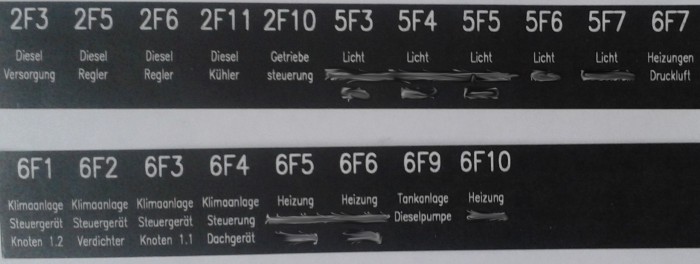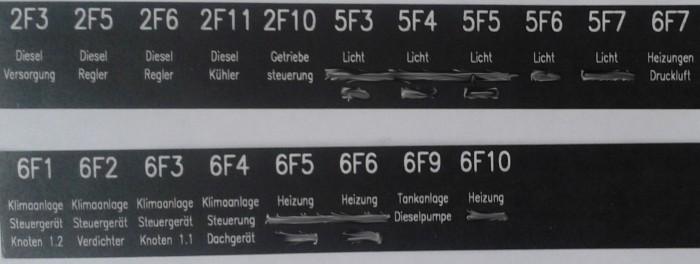
Suche Schrift, ursprünglich verwendet von ELIN
ich suche eine Schriftart die ich auf der Beschriftung einer Sicherungstafel (siehe unten) gefunden habe. Diese Tafel wurde von (VA TECH) ELIN EBG erstellt und beschriftet. Es handelt sich um eine schmale, serifenlose Schrift. Besonderes Merkmal ist die 3.
Ich habe bereits auf verschiedenen Wegen versucht die Schrift online erkennen zu lassen, leider ohne Erfolg. Auch hier in der Schriftenbibliothek bin ich nicht fündig geworden. Vielleicht kann mir von Euch jemand helfen, würde mich sehr freuen! :bow:
DIN Engschrift vermute ich. Zu kaufen gibt es sie zum Beispiel hier.
So weit ich weiß, gibt es die Schrift in verschiedenen Digitalisierungen. In der Wikipedia gibt es ein Bild von einem Stempel zu sehen, der die gewünschte Form der 3 verwendet.
... nicht ganz. Es wird eine Hausschrift eines Graviermaschinen-Herstellers sein.
sind ähnlich, welche genau davon es ist, hab ich jetzt nicht geschaut.
Als digitalisierte Computerfonts wird es die wohl kaum geben.
Was Du meinst vmtl. ist die DIN-Neuzeit-Grotesk nach ... *krustchel* DIN 30.640. Das ist aber keine DIN1451 sondern eine ge-DIN-te Neuzeit Grotesk. Und diese hat ein doppelstöckiges kleines a.
Diese Schrift habe ich sehr oft auf Typenschildern (Großküchen, Blitzschutz) und auf kleinen Warnschildern der E-Werken in den Haushalten gesehen. Subjektive Zuordnung: (Fast?) Alles mit Elektrizität von deutschen Herstellern und bis in die 1970er.
Eher umgekehrt. Solche Schilder wurden (und werden) standardmäßig in mehrschichtige Kunststoffplatten wie diese graviert:
und hierbei wear das sehr wahrscheinlich die Standardschift, die, weil sie der DIN-Schrift am ähnlichsten war, i.d.R auch verwendet wurde. Daher begegnet einen diese Schrift mit der von der DIN-Schrift abweichenden 3 nahezu überalkl, wo wetterfeste Schildere benötigt werden. und das eben schon nlange vor der Zeit, in der man überhaupt außerhalb des Druckgewerbes Satzschriften verwenden konnte
Demzufolge wird wohl kaum eine aktuelle Computerschrift als Basis geDINt haben.
Die von mir genannten Schriften sind keine Computerschriften, denn dazu sind diese zu alt. Mit Deinem Argument müsste man auch die Schriften nach DIN 1451 und anderen Normen ausschließen.
Gut, schließe ich auch die DIN 1451 und DIN16/DIN17 aus, und behaupte einmal, dass hier die Schriften beim Hersteller der Messing-Schablonen (was durchaus auch eines der großen Schriftgießereien gewesen sein kann) speziell hierfür entworfen worden sind. Dabei natürlich die Normschriften im Hinterkopf, jedoch das Normblatt auf dem Zeichentisch liegen zu haben.
Ihr werdet lachen, aber diese Beschriftung ist garnicht geprägt sondern auf Papier gedruckt. Daher hatte ich ursprünglich erwartet diese Schrift recht schnell im Internet in digitaler Form finden zu können. Die Abbildung oben ist ein Foto von einer Kopie.